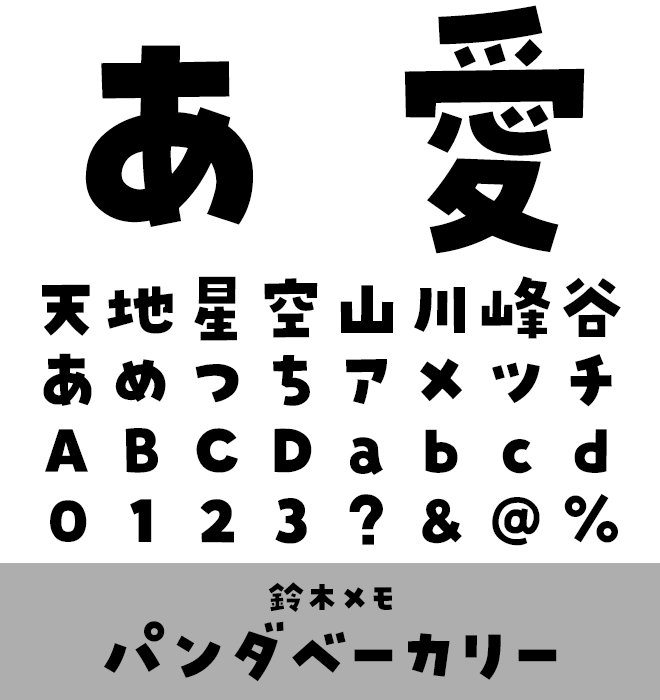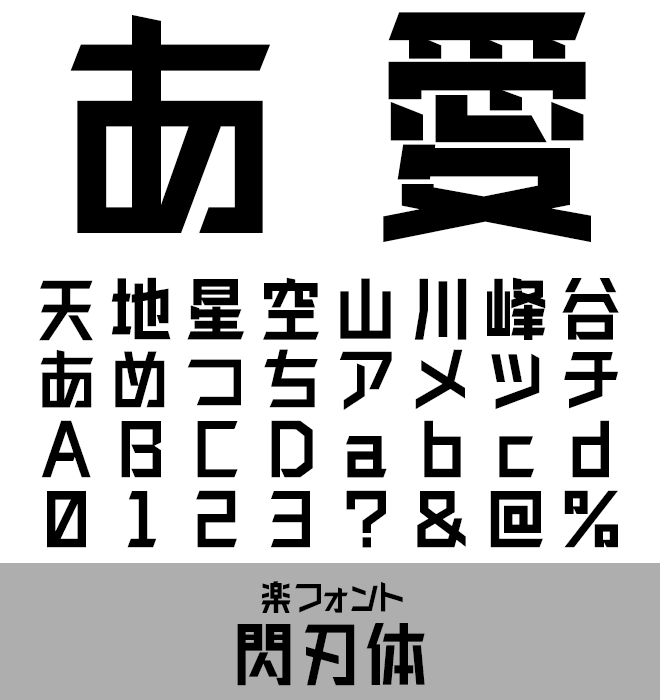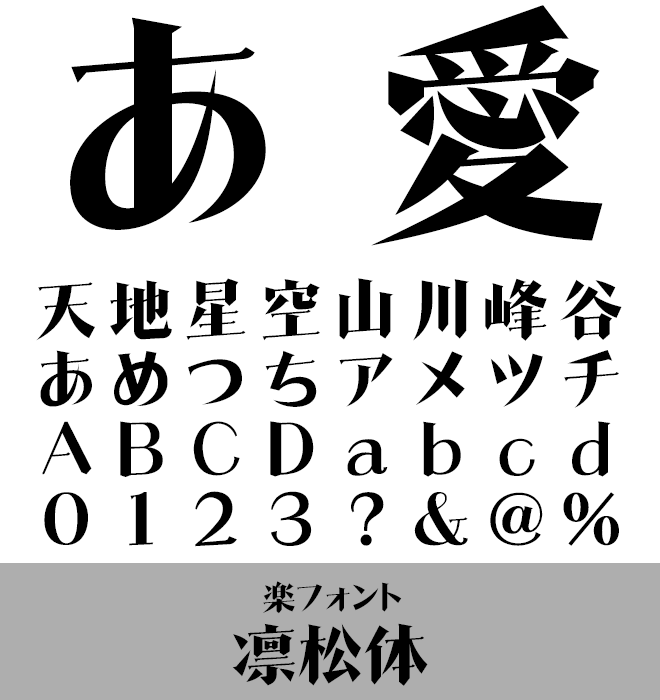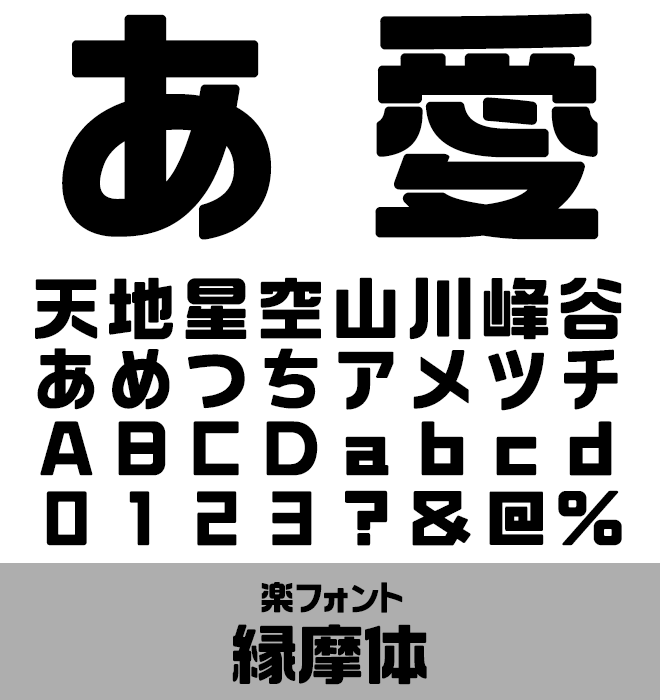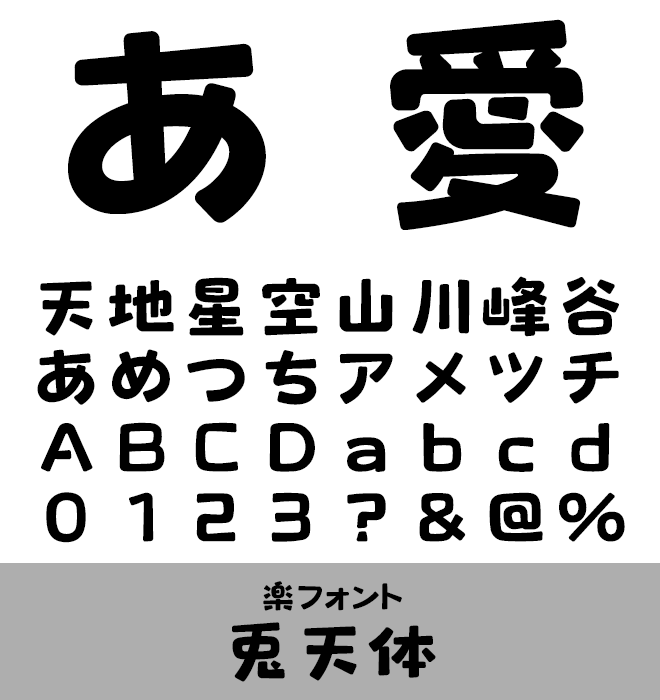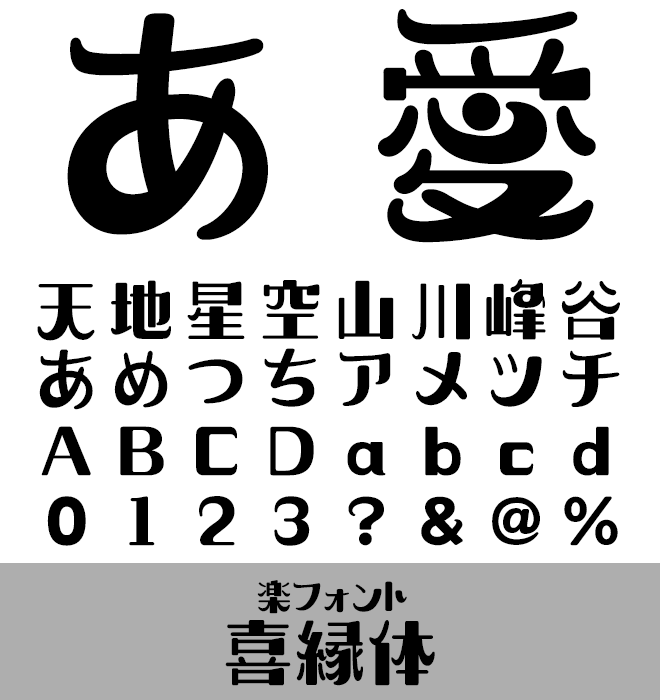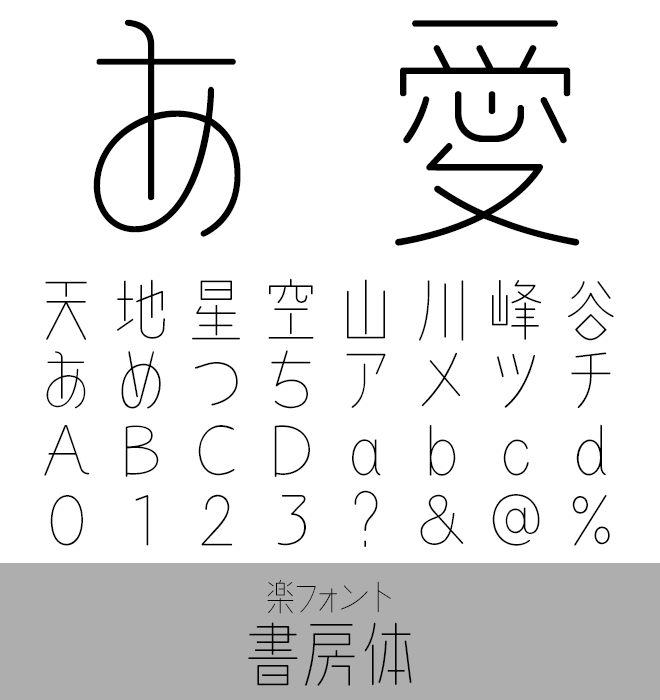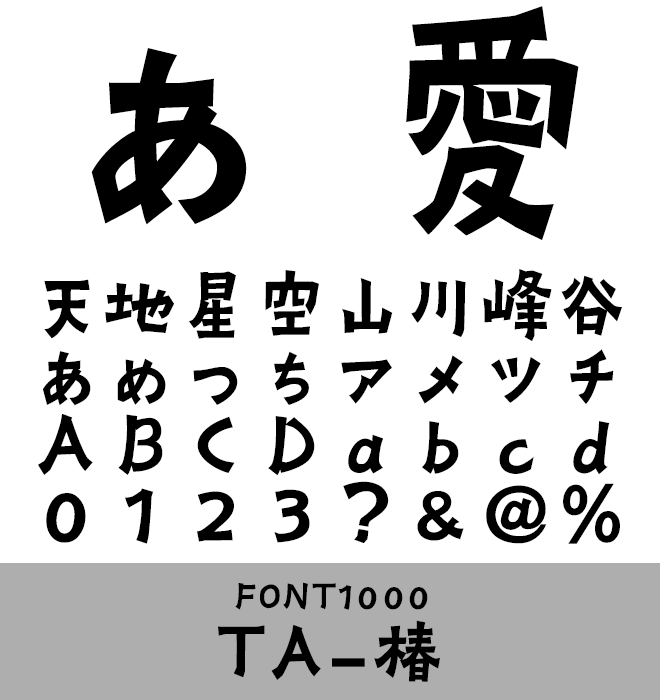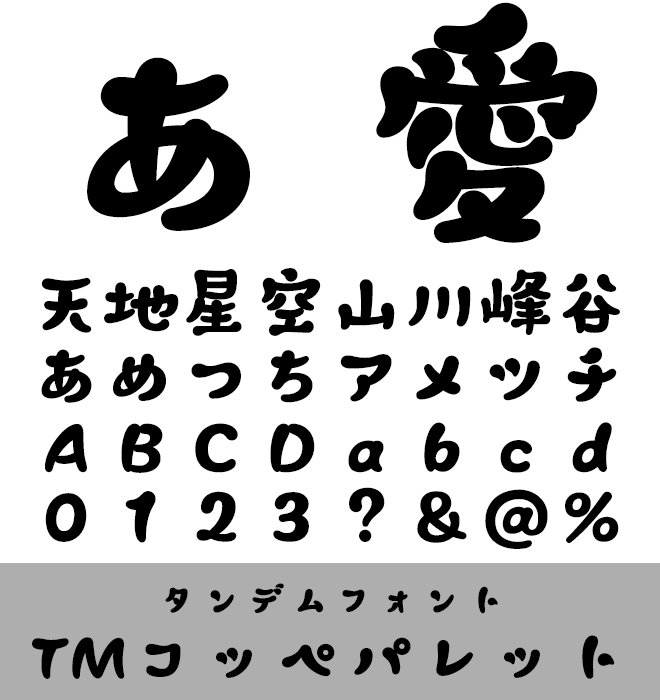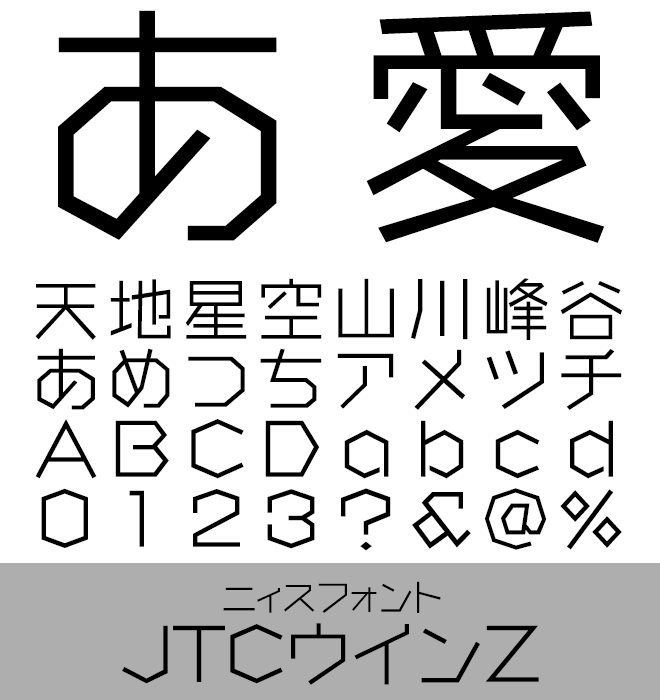
本特集では、価格は控えめながらも、デザイン力に優れた実力派フォントをセレクトしました。予算1万円前後で購入できる書体を中心に、プロの現場でも使用されている信頼のフォントから、趣味の制作やポートフォリオづくりに最適な扱いやすい書体まで、幅広くラインナップ。
プロの目線でも納得のクオリティを備えつつ、初心者でも気軽に使える、見た目も品質も申し分ないフォントを取り揃えてみました。
1万円前後の実力派 デザイン書体
デザイン書体は、個性を際立たせるために生まれたクリエイティブなフォントです。ポップ体や装飾的な文字形は、広告やタイトル、動画制作などで視線を引きつけ、印象に残るデザインを実現します。
遊び心のあるデザインから洗練された高級感のある書体まで、多種多様な選択肢が揃っています。ユニークな雰囲気を演出したい方におすすめです。
実力派 デザイン書体 パンダベーカリー
鈴木メモ
パンダベーカリー
手描きのような自然なリズム感と、しっかりとした太さと手作り感のある可愛らしさ。
実力派 デザイン書体 閃刃体
楽フォント
閃刃体
一寸も揺るがない、力強い筆遣いで貫いた字体が頑丈で、刃のように研ぎ澄まされた硬度のある書体。
実力派 デザイン書体 凛松体
楽フォント
凛松体
「雄松」とも呼ばれる黒松と同様、とどこか洒脱で伊達な男性的な力強さのある書体。
実力派 デザイン書体 縁摩体
楽フォント
縁摩体
少し丸く落とした角は、人の賑わう街の中で生きる文字が時を経て摩耗し、丸くなったような風情を演出。
実力派 デザイン書体 兎天体
楽フォント
兎天体
無邪気に跳ね回るうさぎのような、丸みを帯びたかわいらしい印象の書体。
実力派 デザイン書体 喜縁体
楽フォント
喜縁体
文字の留め・羽が楽しく跳ね上がるようなデザインで、リズミカルで活力のあるカジュアルな書体。
実力派 デザイン書体 書房体
楽フォント
書房体
重心を高く持ち、美しく洗練されたスマートな線で現代的でシャープかつモダンな印象。
実力派 デザイン書体 TA-椿
FONT1000
TA-椿
ビジネス文書、年賀状、案内状、パンフレット、チラシ、プライベート文書などを多彩に表現。
実力派 デザイン書体 TMコッペパレット
タンダムフォント
TMコッペパレット
画数によって大きさが異なる、ふんわりぽってりしたデザイン書体。
実力派 デザイン書体 JTCウインZ
ニィスフォント
JTCウインZ
直線だけで構成された極めて珍しいデザインのゴシック体。
実力派 デザイン書体 JTCじゃんけんU
ニィスフォント
JTCじゃんけんU
ほがらか、楽しい、自然、素朴なイメージ。
実力派 デザイン書体 F1000-DON
FONT1000
F1000-DON
太く安定感のある書体です。縦・横のラインを中心に構成して安定感を強調。
実力派 デザイン書体 F1000-カントリーロード
FONT1000
F1000-カントリーロード
ビジネス文書、年賀状、案内状、パンフレット、チラシ、プライベート文書などを多彩に表現。
実力派 デザイン書体 F1000-クワドラ
FONT1000
F1000-クワドラ
ビジネス文書、年賀状、案内状、パンフレット、チラシ、プライベート文書などを多彩に表現。
実力派 デザイン書体 F1000-漫画チック
FONT1000
F1000-漫画チック
漫画っぽいゴシック、漫画のタイトル風、みたいな書体。
1万円前後の実力派 手書き書体
手書き風のフォントは、温かみや親しみやすさを伝えるのに最適です。リアルな手書き感を追求したものや、デザイン性をプラスしたものなど、用途に応じて選べます。
手書きの柔らかい雰囲気は、ポスターやSNS投稿、個人向けの招待状やグリーティングカードなどで活躍します。見る人の心を引きつける、魅力的なデザインのアクセントとしてお使いください。
花とちょうちょ
鈴木メモ
花とちょうちょ
ペンで書いた手書き文字がベースのフォント。右上りの勢いと何より可愛らしいリアル手書き感。
実力派 手書き書体 空とひこうき
鈴木メモ
空とひこうき
空に長く伸びて行くひこうき雲をイメージした書体で、右上りの勢いとリアルな手書き感。
実力派 手書き書体 波とかもめ
鈴木メモ
波とかもめ
リラックスした雰囲気を持った太め・丸め・ユーモアのある手書きフォント。
実力派 手書き書体 桜と少女体
楽フォント
桜と少女体
ゆったりした気分で、つるつるした紙に細い平筆で描かれた書体。
実力派 手書き書体 友人からの手紙体